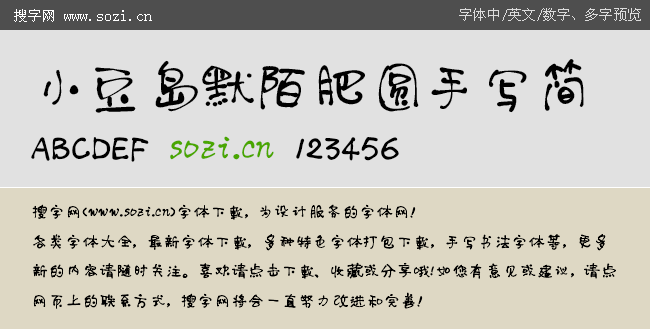
小豆島默陌肥圓手寫簡(jiǎn)
搜字網(wǎng)提供一款小豆島默陌肥圓手寫簡(jiǎn)中文字體下載,小豆島默陌肥圓手寫簡(jiǎn)體是一款非常有個(gè)性的手寫字體,這款字體字形圓潤(rùn),從字體的名字就可以看出,字體美觀大觀 ,適合應(yīng)用于廣告設(shè)計(jì)、名片設(shè)計(jì)、包裝印刷、產(chǎn)品設(shè)計(jì)等應(yīng)用。